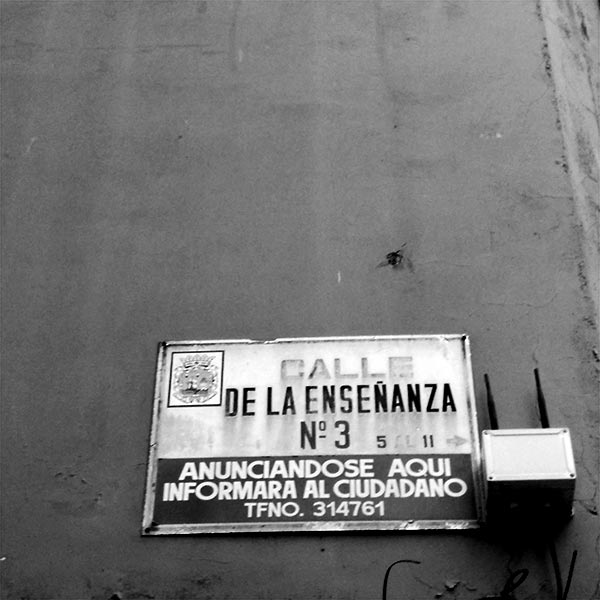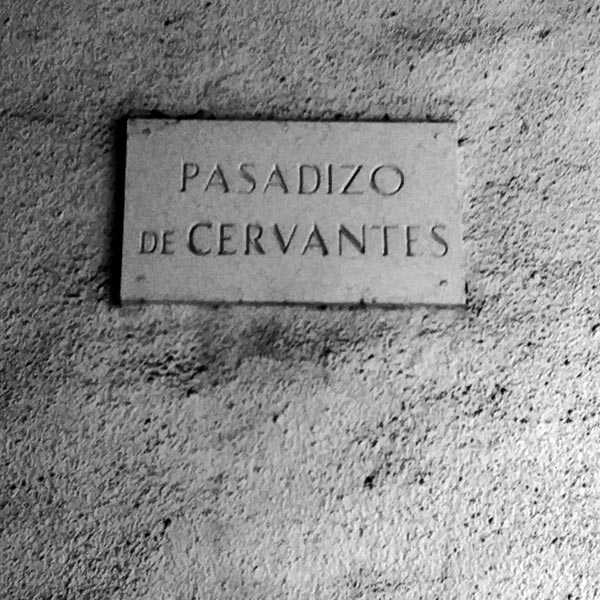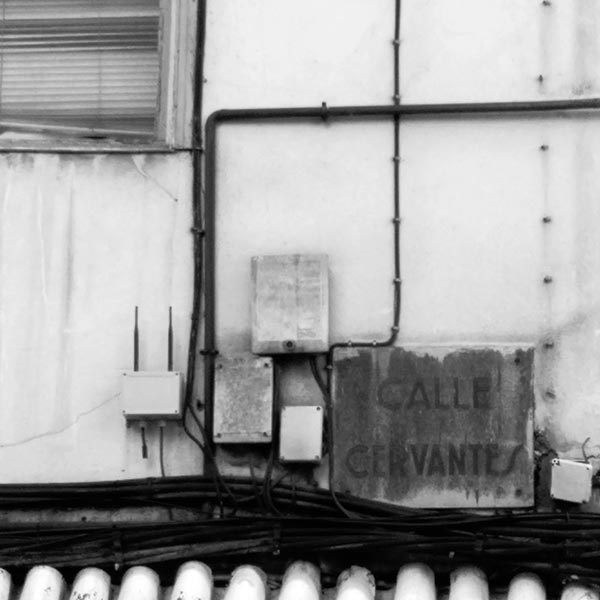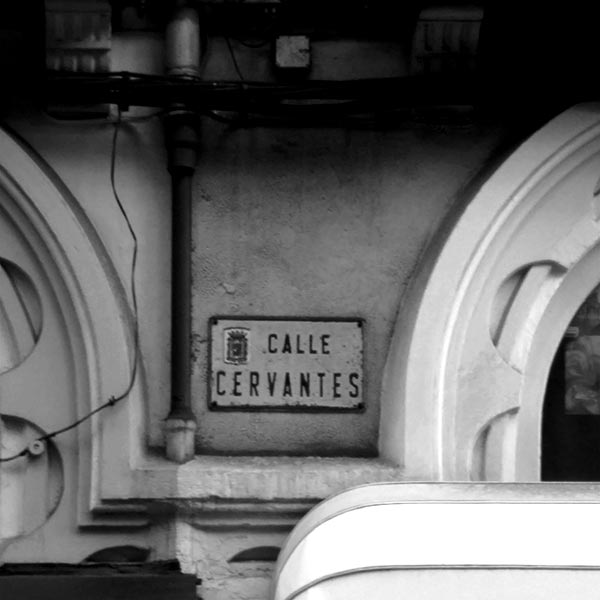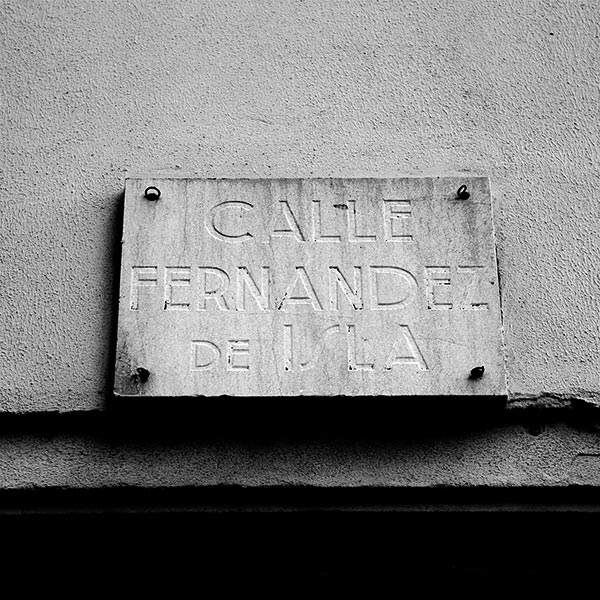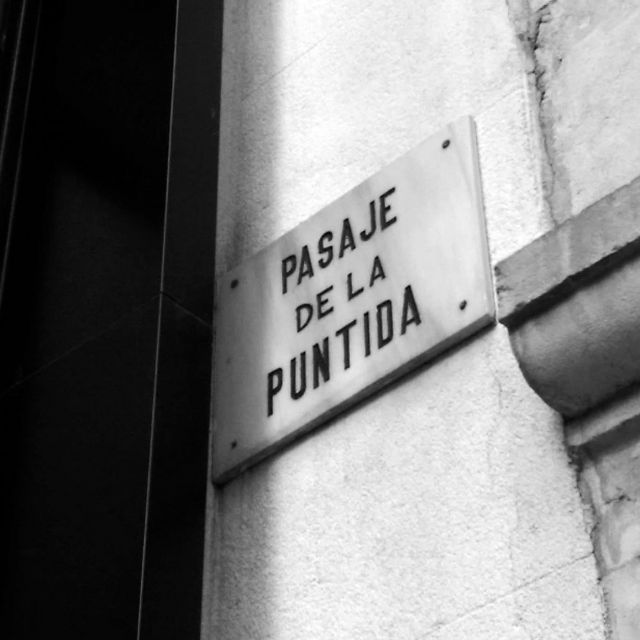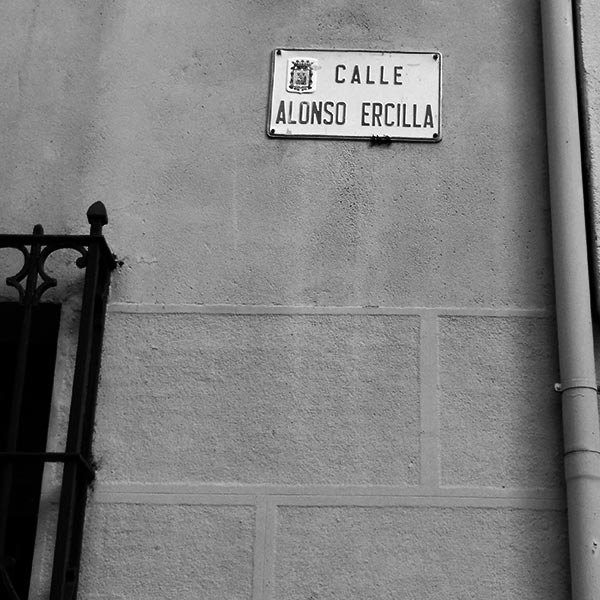
Placas de calle de Santander (II)
En Santander aún podemos encontrar diversas placas de tipología, materiales así como tipografías totalmente diversas que se fueron instalando en la ciudad.
Imagen enviada por Aldo Alonso (el Pasaje de la Puntida está en uno de los accesos a la Plaza Porticada, justo el de la Cámara de Comercio ;))
Imagen enviada por Aldo Alonso